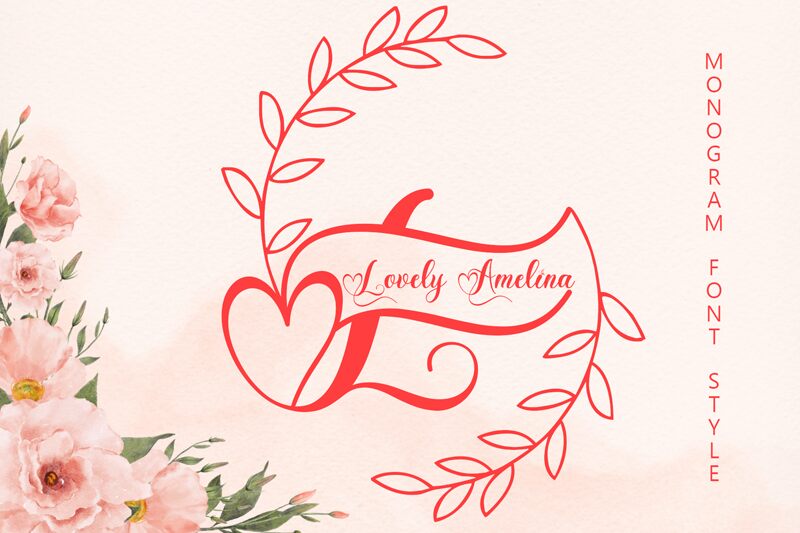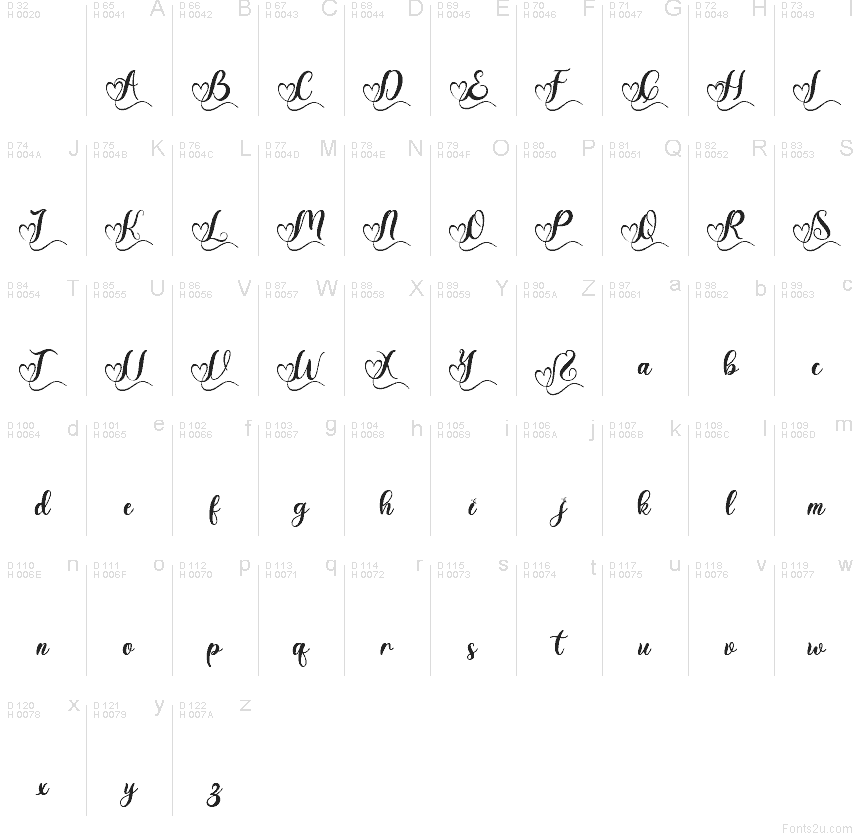
Lovely Amelina Style Demo
Lovely Amelina Style od Yoga Letter je bezplatné psací písmo ideální pro valentýnské projekty, které vyniká svými dlouhými, rozmáchlými smyčkami a plynulým rukopisným rytmem. Písmena se propojují měkkými křivkami, design doplňuje ozdoba ve tvaru srdce a závěrečné tahy přecházejí v elegantní podtržení, které každému slovu dodává romantický a osobitý nádech.
Tento bezplatný font se skvěle hodí pro svatební pozvánky, milostná psaní, přáníčka, loga a grafiku pro sociální sítě, kde dekorativní písmo dokáže skvěle podtrhnout sdělení. Hodí se také pro grafické citáty, obaly produktů nebo sezónní valentýnské vizuály, protože zaoblené tvary a motiv srdce vnášejí do návrhu jasný tematický akcent, aniž by působil příliš rušivě.